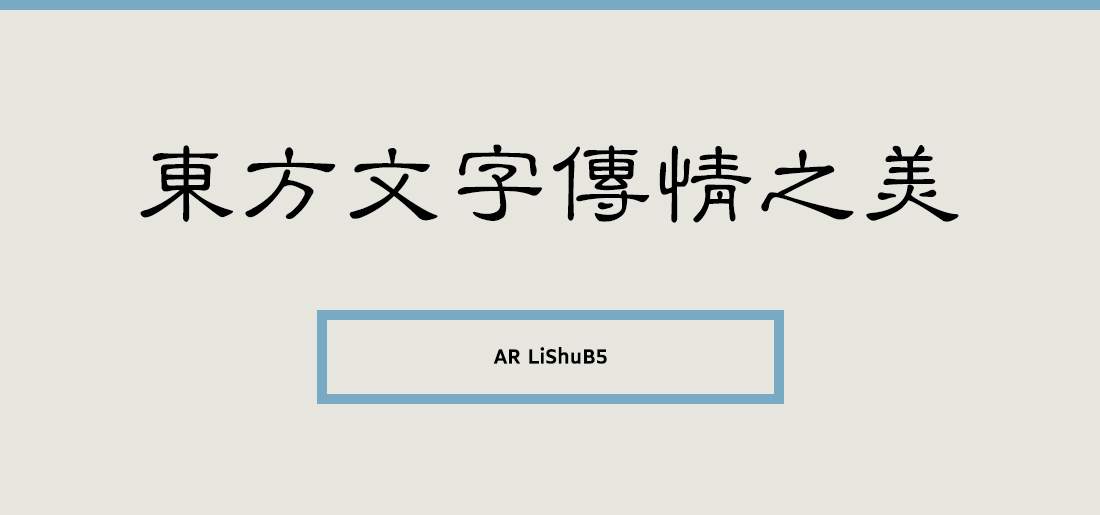
AR LiShuB5
분류 Script
LiShuB5는 당당하면서도 평평하고 수직적 선의 느낌이 살아있는 폰트이다.곧은 골격을 갖고 있으면서도 부드러운 이미지를 나타낼 수 있도록 일본의 폰트 설계에 영향을 받았으며 책, 인사말 카드, 그림 및 시, 신호 및 포스터의 헤드 라인에 적합하다.폰트명 뒤에 붙은 B5라는 표기는 번체의 문자코드인 BIG5를 뜻한다. 번체란 중국을 제외한 대만, 홍콩, 마카오 등의 중화권 국가에서 사용하는 전통적인 모양의 한자다. 중국에서 사용하는 간체(GB)와는 달라 잘못 적용할 경우 글립이 제대로 표기되지 않거나 다른 글립으로 표기되는 문제가 발생할 수 있다.